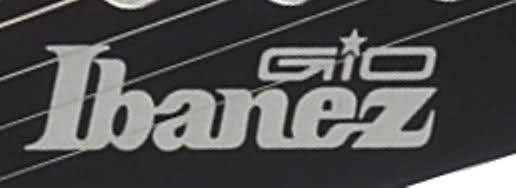
Welche Schriftart wird für das Ibanez-Logo benutzt ?
Mich würde interessieren welche Schriftart für das Ibanez-Logo verwendet wurde:
(Mich interessiert nur das "Ibanez", nicht das "Gio")
Ich habe bei Ibanez-Instrumenten schon die verschiedensten Variationen von diesem Logo gesehen. Ich würde auch sagen, dass es ein Logo ist, keine Schrift (was nicht heißt dass nicht eine Schrift zu grunde liegt).
Die Marke gibt es seit 1957 in dieser Form (japanische Eigentümer), davor bis etwa 1930 in Spanien. Wann aber das Logo entstanden ist und ob man eine Historie dazu finden könnte ... :?
und ich würds auch nicht um die burg nachbauen wollen, nicht weils kompliziert wäre, es sieht einfach scheiße aus! (sorry, aber das musste jetzt raus)